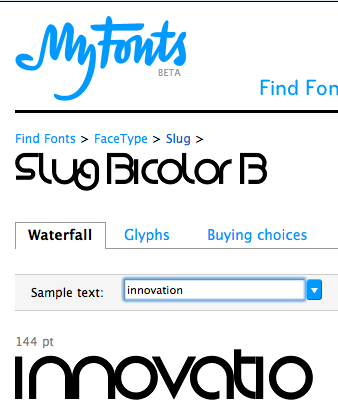
Bitte um Hilfe bei Fontsuche
bitte um Nachhilfe welcher Font das ist. Whatthefont und Identifont waren nicht hilfreich. Den Schriftzug hat ein Grafiker gemacht. Es ist eher unwahrscheinlich, dass er auf einen Wald-und-Wiesen Freefont zurückgegriffen hat. Es sollte demnach was "Richtiges" sein.
Oje - ich hatte gehofft den Font gäbe es - mein Kunde will ihn nämlich kaufen.
Auf die Idee, dass er modifiziert worden ist, bin ich nicht gekommen. Vor allem weil es ein "superschnelles" Projekt war und ich dem Grafiker diesen Aufwand gar nicht zugetraut hab.
Vor allem weil es ein "superschnelles" Projekt war und ich dem Grafiker diesen Aufwand gar nicht zugetraut hab.
Ist weiter gar kein Aufwand. Von der Bauhaus ausgehend, ca. zehn Minuten Arbeit.
Dem Logo dürfte die Slug zugrunde liegen …